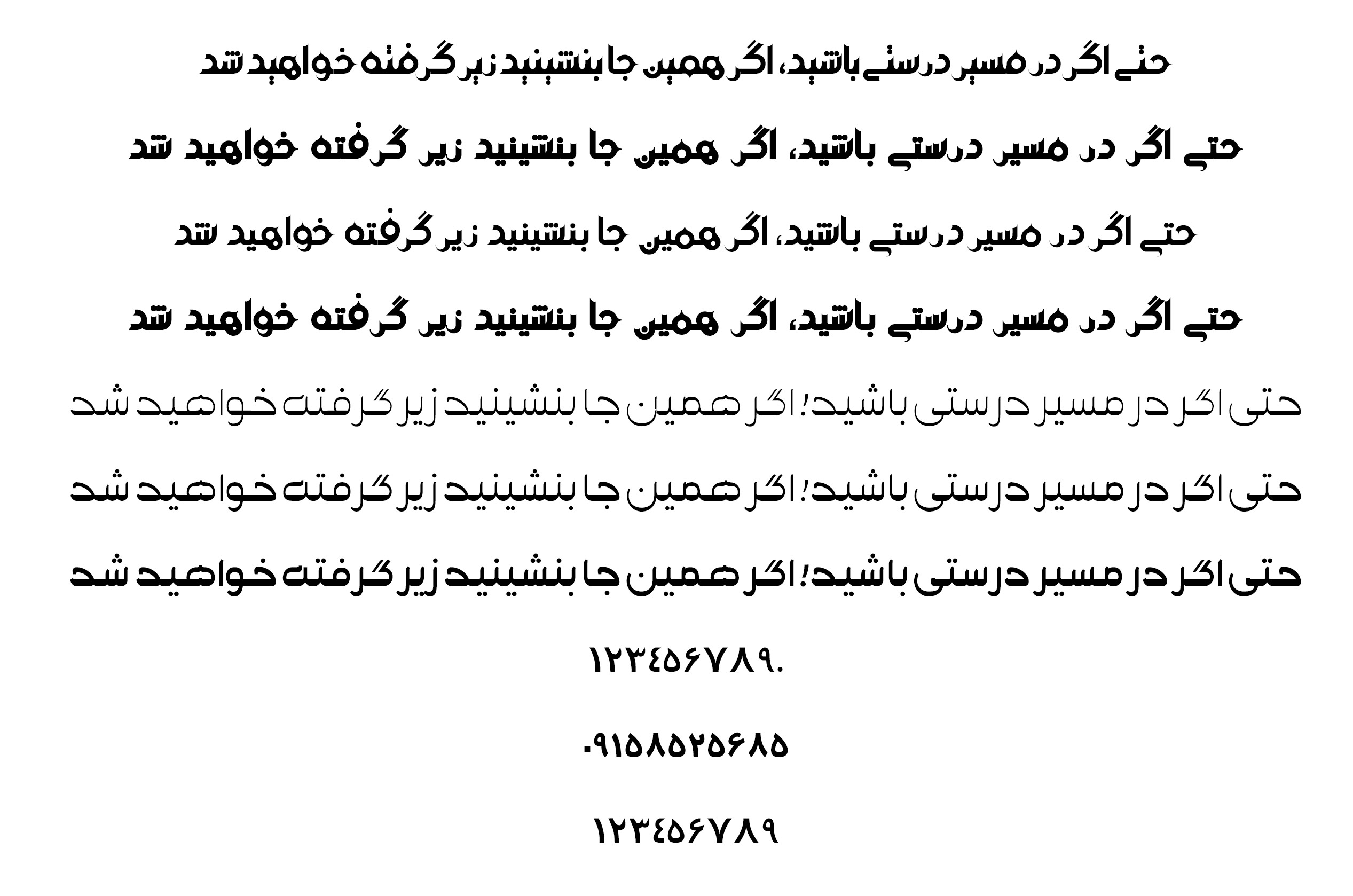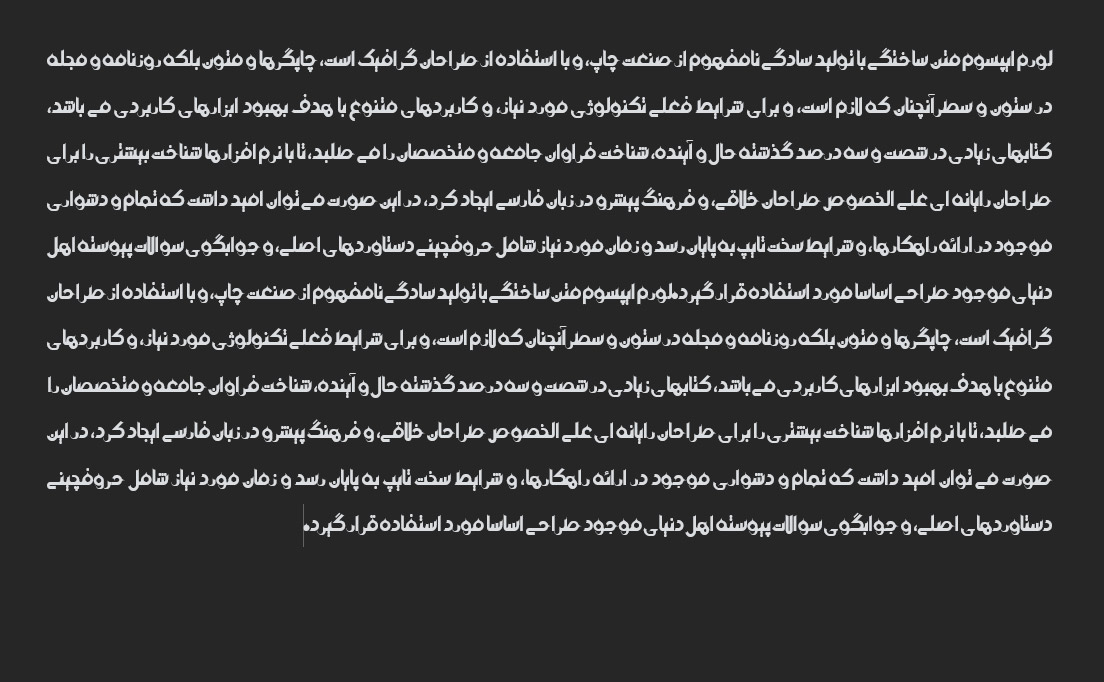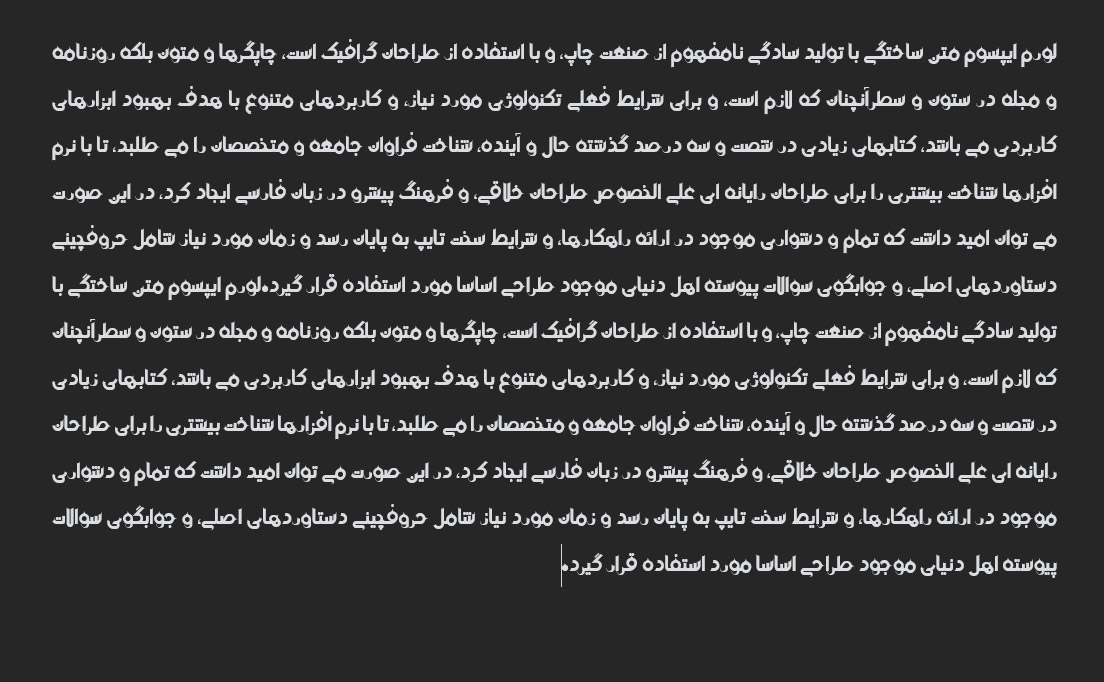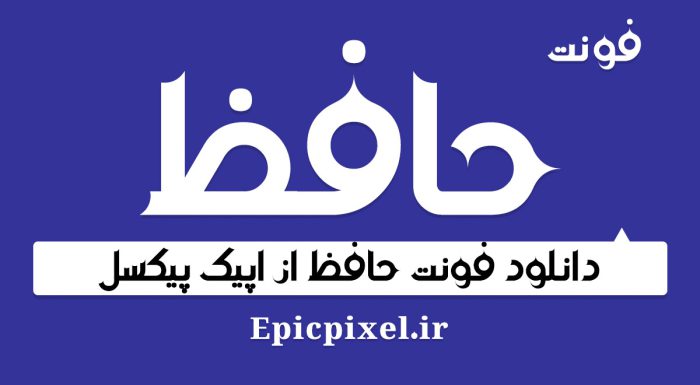
فونت حافظ زیبایی و ظرافت در دنیای نوشتار فارسی
مقدمه
در دنیای طراحی گرافیک و تایپوگرافی، انتخاب فونت مناسب نقشی اساسی در انتقال پیام و ایجاد تاثیرگذاری بصری ایفا می کند. فونت حافظ، یکی از فونت های محبوب و پرکاربرد در میان طراحان گرافیک فارسی، با طراحی ظریف و متناسب خود، زیبایی و خوانایی را به متن فارسی می بخشد. در این مقاله، به معرفی ویژگی ها، کاربردها و اهمیت فونت حافظ در دنیای طراحی گرافیک فارسی می پردازیم.
ویژگی های فونت حافظ
فونت حافظ، با طراحی ظریف و چشم نواز خود، در گروه فونت های sans-serif قرار می گیرد. این فونت دارای ویژگی های متمایز زیر است:
خوانایی عالی در سایزهای مختلف: فونت حافظ به دلیل شکل حروف و فاصله گذاری مناسب، خوانایی عالی را در سایزهای مختلف، از متن های ریز تا عناوین بزرگ، ارائه می دهد. این ویژگی باعث می شود که فونت حافظ برای استفاده در انواع پروژه های طراحی گرافیک، از جمله کتاب، مجله، وب سایت و رابط کاربری، مناسب باشد.
مناسب برای استفاده در متون طولانی و کوتاه: طراحی متناسب فونت حافظ باعث می شود که متن فارسی در استفاده طولانی خسته کننده و نامفهوم نباشد. همچنین، این فونت در متن های کوتاه نیز به خوبی خودنمایی می کند.
دانلودسازگاری با انواع رسانه ها، از جمله چاپی و دیجیتال: فونت حافظ به گونه ای طراحی شده است که در انواع رسانه ها، از جمله چاپی و دیجیتال، به خوبی نمایش داده می شود.
کاربردهای فونت حافظ
فونت حافظ دارای کاربردهای گسترده ای در دنیای طراحی گرافیک فارسی است. این فونت را می توان در انواع پروژه های زیر استفاده کرد:
طراحی کتاب، مجله و سایر نشریات چاپی: فونت حافظ به دلیل خوانایی عالی و ظرافت طراحی، برای استفاده در کتاب ها، مجلات و سایر نشریات چاپی بسیار مناسب است. این فونت باعث می شود که متن فارسی در این نشریات به زیبایی و وضوح نمایش داده شود.
طراحی وب سایت و رابط کاربری: فونت حافظ به دلیل سازگاری با انواع رسانه ها، برای استفاده در وب سایت ها و رابط کاربری نیز مناسب است. این فونت باعث می شود که متن فارسی در وب سایت ها و رابط کاربری به زیبایی و وضوح نمایش داده شود و تجربه کاربری بهتری را برای کاربران ایجاد کند.
طراحی سربرگ، کارت ویزیت و سایر اقلام اداری: فونت حافظ به دلیل زیبایی و ظرافت طراحی، برای استفاده در سربرگ، کارت ویزیت و سایر اقلام اداری نیز مناسب است. این فونت باعث می شود که این اقلام اداری به زیبایی و ظرافت بیشتری دیده شوند.
طراحی پوستر، بروشور و سایر مواد تبلیغاتی: فونت حافظ به دلیل خوانایی عالی و ظرافت طراحی، برای استفاده در پوستر، بروشور و سایر مواد تبلیغاتی نیز مناسب است. این فونت باعث می شود که پیام تبلیغاتی به زیبایی و وضوح بیشتری به مخاطبان منتقل شود.
طراحی لوگو و نشان تجاری: فونت حافظ به دلیل زیبایی و ظرافت طراحی، برای استفاده در طراحی لوگو و نشان تجاری نیز مناسب است. این فونت باعث می شود که لوگو و نشان تجاری به زیبایی و ظرافت بیشتری دیده شوند و تاثیرگذاری بیشتری بر مخاطبان داشته باشند.
نسخه های مختلف فونت حافظ
فونت حافظ در سه نسخه Light، Regular و Bold ارائه شده است. هر یک از این نسخه ها دارای ویژگی های خاص خود هستند و برای کاربردهای متفاوتی مناسب هستند.
نسخه Light: این نسخه از فونت حافظ دارای ضخامت کمتری نسبت به نسخه های دیگر است و برای استفاده در متن های طولانی و عناوین کوچک مناسب است.
نسخه Regular: این نسخه از فونت حافظ دارای ضخامت متوسطی است و برای استفاده در متن های معمولی و عناوین متوسط مناسب است.
نسخه Bold: این نسخه از فونت حافظ دارای ضخامت بیشتری نسبت به نسخه های دیگر است و برای استفاده در عناوین بزرگ و متن های برجسته مناسب است.
مقایسه فونت حافظ با دیگر فونت های فارسی
فونت حافظ از نظر ویژگی های ظاهری و فنی، شباهت هایی با فونت های فارسی دیگر مانند فونت نازنین و فونت ایران تایپ دارد. با این حال، فونت حافظ دارای ویژگی های متمایز زیر است که آن را از دیگر فونت های فارسی متمایز می کند:
ظرافت و زیبایی بیشتر در طراحی حروف: فونت حافظ دارای طراحی ظریف و چشم نوازتری نسبت به دیگر فونت های فارسی است. این ویژگی باعث می شود که متن فارسی در استفاده طولانی خسته کننده و نامفهوم نباشد.
خوانایی بهتر در سایزهای مختلف: فونت حافظ دارای خوانایی بهتری در سایزهای مختلف نسبت به دیگر فونت های فارسی است. این ویژگی باعث می شود که فونت حافظ برای استفاده در انواع پروژه های طراحی گرافیک، از جمله کتاب، مجله، وب سایت و رابط کاربری، مناسب باشد.
تاثیر فونت حافظ بر زیبایی و خوانایی متن فارسی
فونت حافظ با طراحی ظریف و متناسب خود، زیبایی و خوانایی متن فارسی را افزایش می دهد. این فونت باعث می شود که متن فارسی در انواع پروژه های طراحی گرافیک، از جمله کتاب، مجله، وب سایت و رابط کاربری، به زیبایی و وضوح بیشتری نمایش داده شود.
نتیجه گیری
فونت حافظ یک فونت فارسی زیبا و خوانا است که دارای کاربردهای گسترده ای در دنیای طراحی گرافیک است. این فونت می تواند به طراحان گرافیک کمک کند تا پیام خود را به زیبایی و وضوح بیشتری به مخاطبان منتقل کنند. با انتخاب هوشمندانه نسخه مناسب فونت حافظ، می توان زیبایی و خوانایی متن فارسی را افزایش داد.